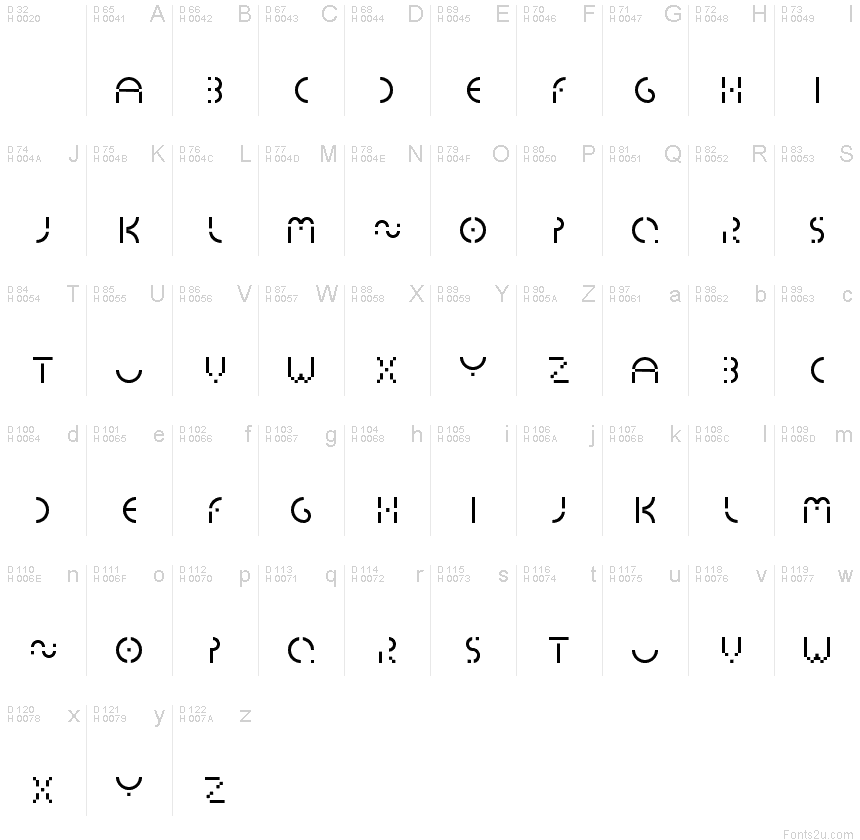
Essedicom è un carattere display futurista e gratuito, costruito su una geometria circolare e tratti bruscamente interrotti. Le sue aperture e i ripetuti tagli orizzontali conferiscono alle lettere un ritmo modulare e simile a un segnale, bilanciando la precisione dell'era spaziale con un'impronta decisamente sperimentale.
La sua struttura segmentata crea un effetto visivo codificato nel branding tecnologico, nelle grafiche per la musica elettronica e nelle schermate dei titoli dei giochi. Questo font gratuito si presta inoltre a poster di fantascienza, grafiche per il lancio di app e identità di eventi, dove la sua geometria essenziale evoca interfacce, forme orbitali o diagrammi tecnici.